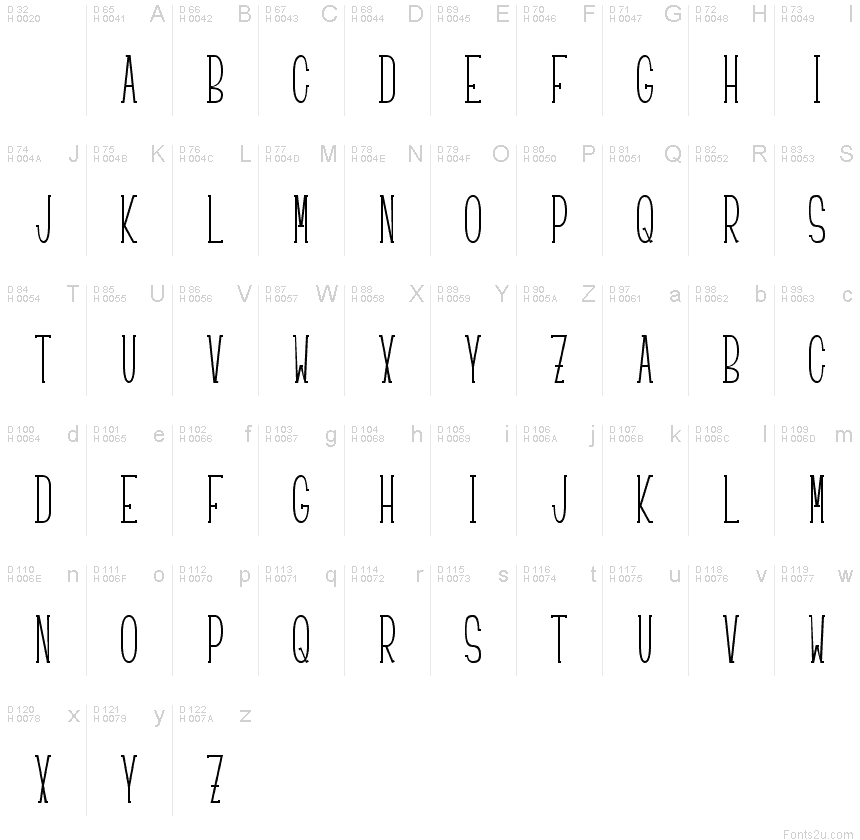
Ciao od Dibujado to darmowy, retro font typu display, który rozciąga litery w eleganckie, druciane kolumny z zaokrąglonymi, rurowymi łukami. Stylistyką przypomina ręcznie szkicowane, neonowe szyldy vintage – jest wysoki, pełen lekkości i cudownie teatralny. Jego ultra-wąski rytm przyciąga wzrok ku górze, sprawiając, że każde słowo wygląda jak stylowy nagłówek z afisza.
Dzięki Ciao krótkie frazy stają się obiektami graficznymi, dlatego font ten świetnie sprawdza się na plakatach, okładkach albumów, w brandingu modowym, menu koktajlowych, logotypach butików oraz odważnych grafikach do mediów społecznościowych. Ten darmowy font najlepiej prezentuje się w dużych rozmiarach, gdzie jego cienkie linie pozostają ostre i wyraziste. Zestawiaj Ciao z prostym, geometrycznym fontem bezszeryfowym w mniejszych tekstach, aby zachować czytelność układu, pozwalając jednocześnie, by jego retro osobowość grała pierwsze skrzypce.
a *dibujado* font
Ciao